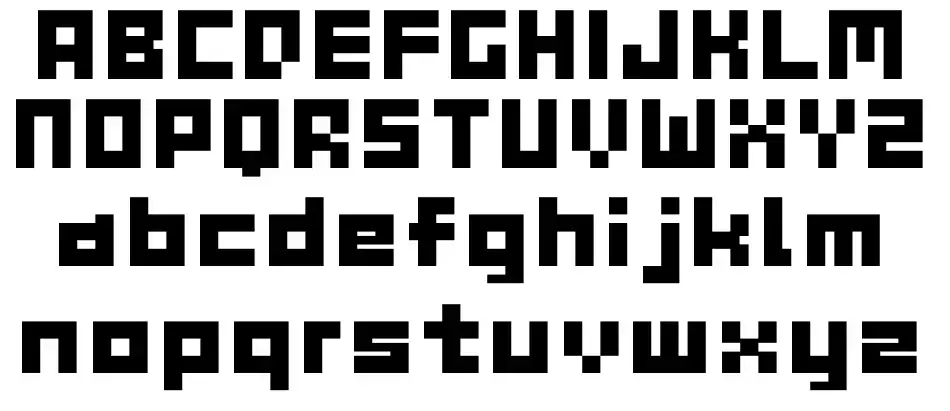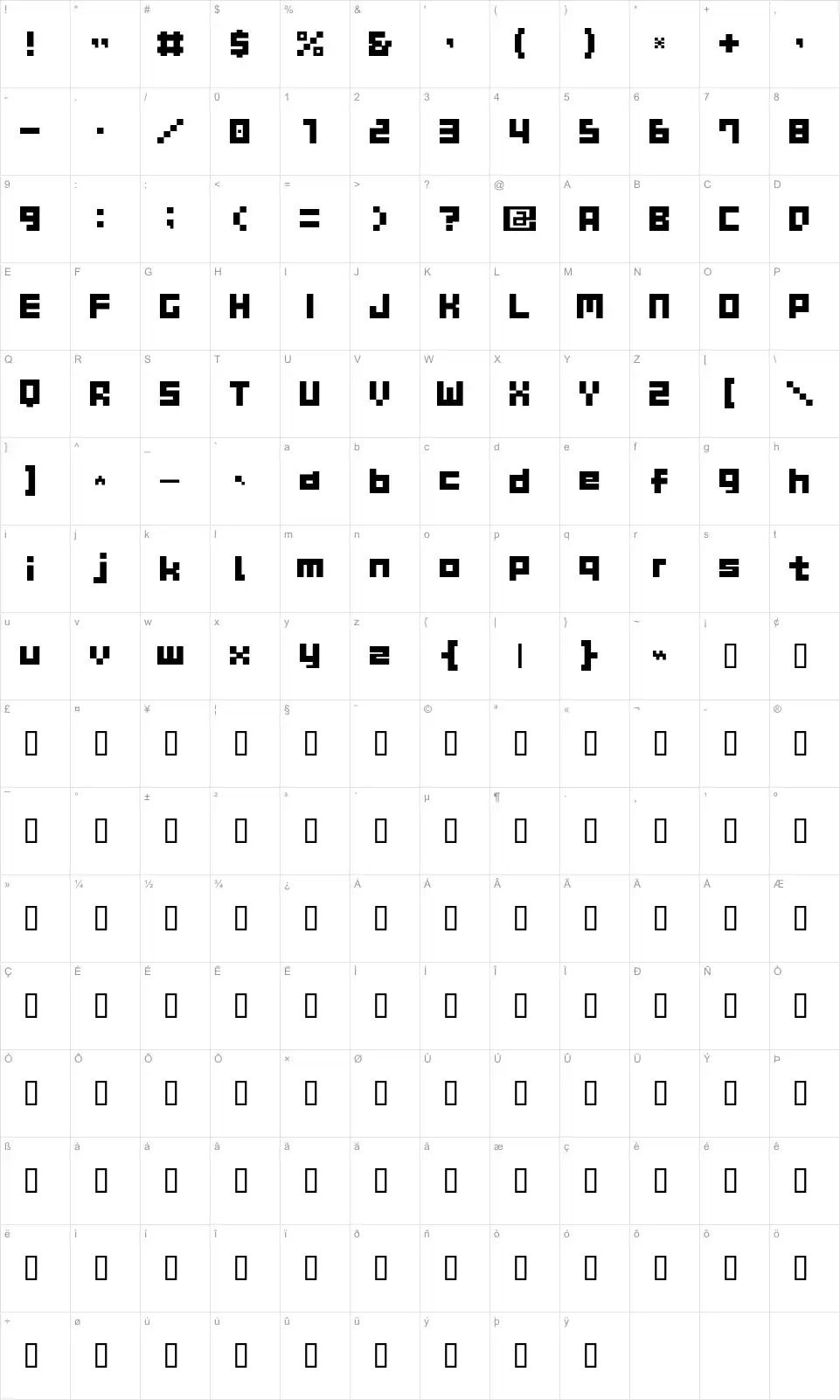
A fonte Gau Font Cube, criada pelo estúdio de arte gráfica Graphic Arts Units, é uma escolha perfeita para ambientes tecnológicos e futuristas. Adicionada em 11 de julho de 2022, esta fonte da categoria Techno, classificada como Square, apresenta um estilo arrojado e inovador. Para aqueles que desejam experimentar a aparência da Gau Font Cube antes de aplicá-la, o site do estúdio oferece a possibilidade de gerar um preview de texto personalizado online. A fonte está disponível em formato TTF e está licenciada livremente, tornando-a acessível para designers de todo o mundo. Com downloads contabilizados em 1787, a Gau Font Cube é um ícone do design tecnológico. Como fonte de formato compacto de 21 KB, é especialmente adequada para projetos digitais e sites web. Para mais informações e para baixar a fonte, visite o site do estúdio: http://www.interq.or.jp/ox/gau/gau_pra.
Categoria: Techno › Square
Designer: Graphic Arts Units